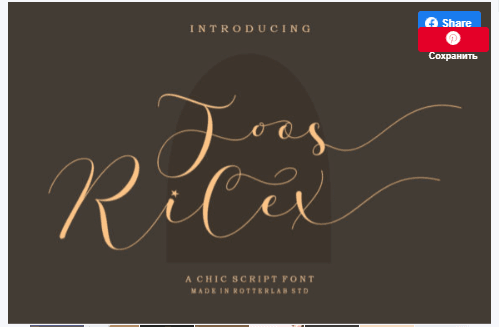
Joos Rilex Font
Joos Rilex - красивый легкий рукописный шрифт с уникальным ощущением и потрясающим воздействием. Он придаст изюминку любому дизайнерскому проекту, который вы желаете создать! Этот шрифт имеет кодировку PUA, что означает, что вы можете легко получить доступ ко всем удивительным глифам и лигатурам!